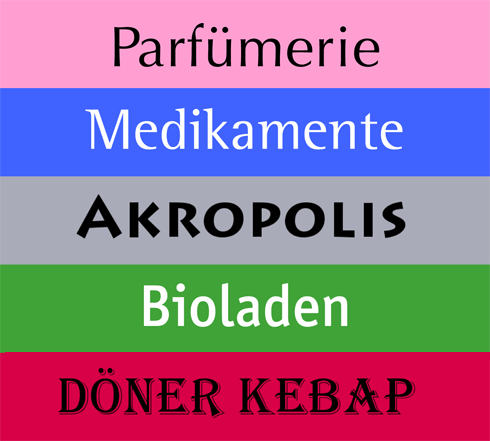
Es gibt Berufszweige, die gerne auf die immer gleiche Schrift zurückgreifen: siehe Branchenschriften. Die Lieblingsschrift der Kosmetikbranche ist seit vielen, vielen Jahren Optima. Durchaus passend zur pharmazeutischen Industrie ist deren Liebling Rotis Serif und Semi-Serif, zwei Schriften aus der Retorte. Ob Athener Grill, Akropolis oder Restaurant Hellas … eine Lithos an der Hauswand verspricht genau das, was die Küche halten wird. Biomarken und Bioläden erklären die Qualität ihrer Produkte, durchaus angemessen, am liebsten mit der informellen ITC Officina, aber bitte doch nicht alle. Sehr beliebt bei Imbissbuden mit osteuropäischem Einschlag: Algerian. Wer kennt weitere Branchen, denen es an typografischer Imagination mangelt? Bitte Kommentar mit Bild …
Ich glaube, die Trajan in Filmtiteln ist uns allen bekannt, vielleicht sogar aus dem exzellenten Kurzfilm “Etched in Stone” (bei Veer).
Design-Irgendwas: Helvetica.
„Codex“ für Yoga und Esoterik.
“Libra” für jede Art von Irish Pub, Mittelaltermarkt, Met-Stand, Sonnenwendfeier-Plakat…
Der Officina trend kommt vielleicht auch daher, dass wir (damals war ich bekanntlich bei MetaDesign) seinerzeit (ab 1992) diese damals nagelneue und „coole“ schrift für die lebensmittelkette Tegut genommen hatten. Tegut war eine der ersten firmen im lebensmitteleinzelhandel, die auf bio setzten und in der szene sehr einflussreich waren. Das hat folgen gehabt…
Wir arbeiten wieder für Tegut und werden wohl die schrift ändern, weil die ganze branche nachgezogen hat.
Computer- und Drucker”paradiese”: Comic Sans
Ärzte: Dutch
für gas-wasser-etc.-installateure: bauhaus. vorzugsweise in rot oder blau. oder beides.
Imago für Hoch- und Tiefbau. In Bold und Extra Bold natürlich. Bodenständig – passend.
Die Rotis findet man natürlich auch bei vielen kulturellen Institutionen: Kulturbüros, Theater usw.
Snowboard- und Skateboardfirmen »müssen« hingegen die Helvetica benutzen.
Bei Filmplakaten ist neben der Trajan auch die Bank Gothic sehr beliebt.
garamond für schulen mit humanistischem/altsprachlichen anspruch. überhaupt für alle interessant, die beständigkeit, klasse, ständebewusstsein, ultraseriösität etc. ausdrücken wollen (antiquare, antiquitäten-händler, anwälte, …).
“Bertram” für das Bowlingcenter am Rande der Stadt, aber auch Spielzeugläden
Gotham – Für alle die Borsche, Hort oder Lombardo sein wollen :)
Immer gerne genommen für eher langweilige Frisörsalons: Peignot
Wobei die nur in Versalien recht erträglich ist. Ach ja, der gute alte Pfennig :-)
Ja und natürlich nicht zu vergessen: die DIN Mittelschrift sehr beliebt beim Designernachwuchs ;)
Brush Script für kleine Tanzschulen, Massage-und Maniküre-Studios, ambulante Pflegedienste, Seniorenheime …
Erik, was? mein tegut? ihr ändert das Design?
Beruhigend, dass ihr das macht, aber bütte geht gut mit ihm um. Die Umgestaltung des Marktplatzes vor ein, zwei Jahren und manche Verpackung der letzten Zeit sind schlimm genug, Ich bin so froh, dass sie, im Gegensatz zu anderen Ketten, ihr CD seit über 15 Jahren weitgehend unangetastet gelassen haben. Wenn ich noch im consumer panel wäre, würde ich mich dafür einsetzen, dass man dort auch den Schriftgeschmack untersucht und nicht nur das neue Müesli.
(ein Wort und schwupps werde ich vom Gestalter, der sich über neue Aufträge freut, zum konservativen Benutzer, der Änderungen an seiner Lieblingsmarke scheut … )